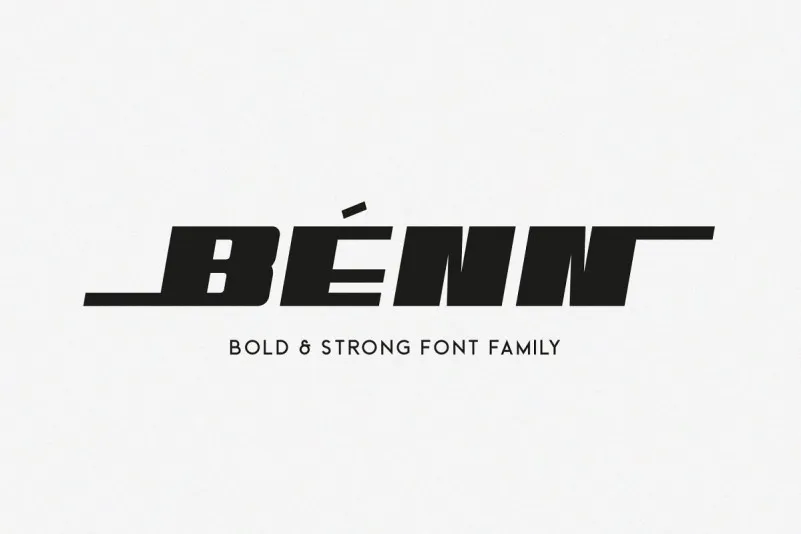
A ‘Benn Sans Serif Font Family’ é uma escolha perfeita para quem busca um estilo moderno e clean, mas com um toque mais pesado. Ideal para criar títulos impactantes e headlines poderosos. Inspirada no formato de um automóvel, ela possui um design robusto e sem compromissos, destacando-se através das formas bem controladas e dos suaves detalhes que dão vida aos caracteres. Uma combinação elegante entre linhas rígidas e curvas fluidas torna-a perfeita para qualquer aplicação de identidade visual. Seus diferentes pesos permitem que você explore uma ampla gama de possibilidades, enquanto os alternativos de letras oferecem um toque moderno e sofisticado a qualquer projeto. Seja em logomarcas, panfletos, revistas ou filmes, esta fonte tem tudo o que você precisa para reforçar sua marca com estilo e clareza.